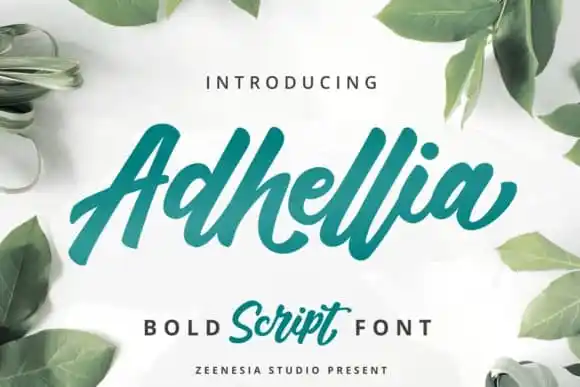
Adhellia Script Font é uma elegante escolha para designers digitais a procura de uma fonte com flow natural e sofisticado. Ela foi criada pelo designer Hamilton, possuindo um estilo bem desenhado que traz uma ressonância única à qualquer projeto. Esta fonte é especialmente adequada para criações em estilos como branding, assinaturas, convites de casamento, promoção, embalagens de produto e muito mais. Adhellia mantém uma simplicidade moderna ao mesmo tempo que preserva um caráter autêntico. Seu design vem da fonte designer Zeenesia e traz todo o seu estilo para a Adhellia. Ela é descrita como uma fonte com traços suaves e escrita à mão, criando uma sensação de confiança e fluidez que certamente fará suas criações realmente “viverem” em qualquer aplicação. Com um PUA (Portable User Access) codificado na fonte, você tem a liberdade de acessar todos os gílios e espirais com facilidade. Adhellia é uma fonte moderna que oferece personalidade sem perder a autenticidade necessária para qualquer projeto, tornando-a uma opção perfeita para diversos tipos de trabalhos e projetos digitais.